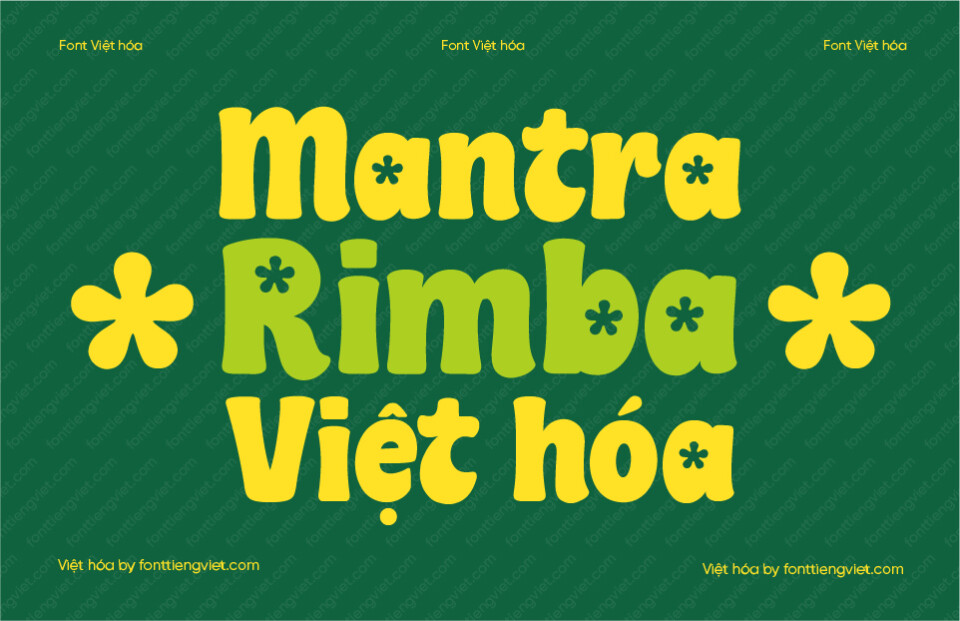
Font Việt hóa 1FTV VIP Mantra Rimba
Giới thiệu về Font Việt hóa 1FTV VIP Mantra Rimba
Trong thế giới đồ họa hiện đại, việc tìm kiếm một bộ Font Miễn Phí có phong cách độc đáo luôn là ưu tiên hàng đầu của các nhà thiết kế. Font Việt hóa 1FTV VIP Mantra Rimba là một tác phẩm nghệ thuật chữ viết mang đậm hơi thở của thiên nhiên và sự hoang dã. Bộ font này không chỉ giữ nguyên được những nét vẽ thô mộc, mạnh mẽ của phiên bản gốc mà còn được tối ưu hóa hoàn toàn cho bảng mã tiếng Việt. Điều này giúp người dùng dễ dàng ứng dụng vào các dự án truyền thông, làm banner hay các bài thuyết trình học đường mà không lo lỗi hiển thị dấu câu.
Tại sao nên chọn Font Việt hóa 1FTV VIP Mantra Rimba?
Đặc điểm nổi bật nhất của Font Việt hóa 1FTV VIP Mantra Rimba chính là cấu trúc chữ cái được cách điệu một cách tinh tế. Các đường nét mô phỏng hình dáng của rễ cây và rừng rậm, tạo nên một cảm giác vừa huyền bí vừa cuốn hút. Đây là lựa chọn lý tưởng cho những ai muốn truyền tải thông điệp về môi trường, phiêu lưu hoặc các chủ đề sáng tạo cần sự phá cách. Việc sử dụng bộ font này sẽ giúp sản phẩm của bạn trở nên chuyên nghiệp và khác biệt hoàn toàn so với các phông chữ phổ thông khác.
Cách ứng dụng Font Việt hóa 1FTV VIP Mantra Rimba hiệu quả
Để tận dụng tối đa vẻ đẹp của bộ chữ, bạn nên sử dụng nó cho các tiêu đề lớn hoặc các cụm từ ngắn cần tạo điểm nhấn. Với độ tương phản cao và hình khối rõ rệt, font chữ này cực kỳ nổi bật trên các nền ảnh phong cảnh hoặc màu sắc trung tính. Ngoài ra, các bạn học sinh và giáo viên cũng có thể dùng phông chữ này để trang trí báo tường hoặc làm bìa tiểu luận thêm phần sinh động.
Lưu ý khi sử dụng trong thiết kế đồ họa
Mặc dù rất đẹp mắt, nhưng người dùng cần lưu ý không nên sử dụng bộ font này cho các đoạn văn bản dài để đảm bảo khả năng đọc tốt nhất. Hãy kết hợp nó với một phông chữ không chân đơn giản để tạo nên sự cân bằng cho tổng thể bố cục. Hy vọng rằng với Font Miễn Phí, Font Việt Hóa, Font Việt hóa 1FTV VIP Mantra Rimba, bạn sẽ có thêm nhiều cảm hứng mới cho những dự án sáng tạo sắp tới của mình.